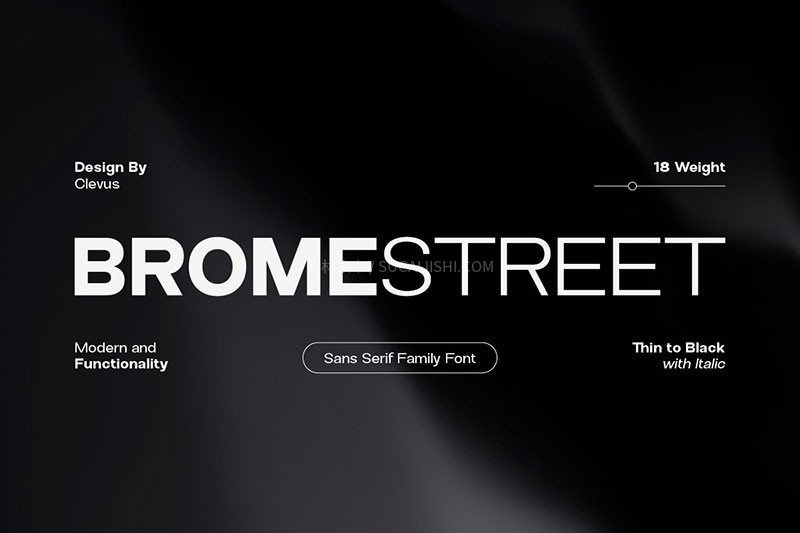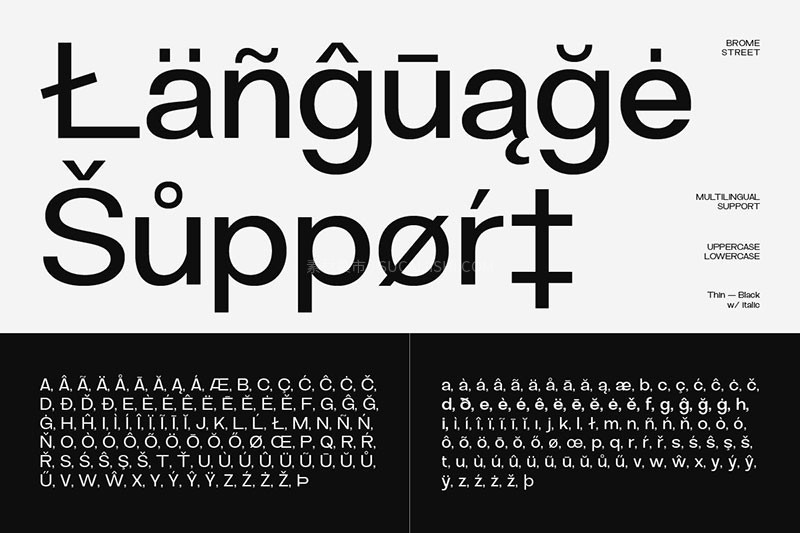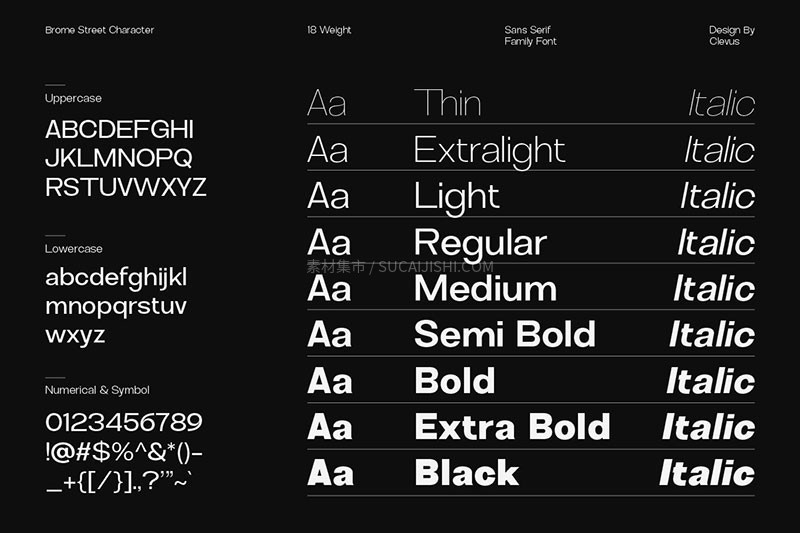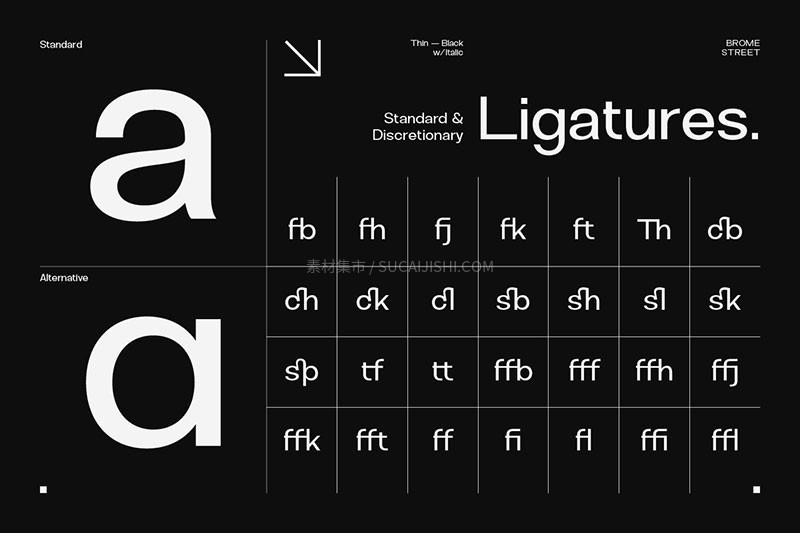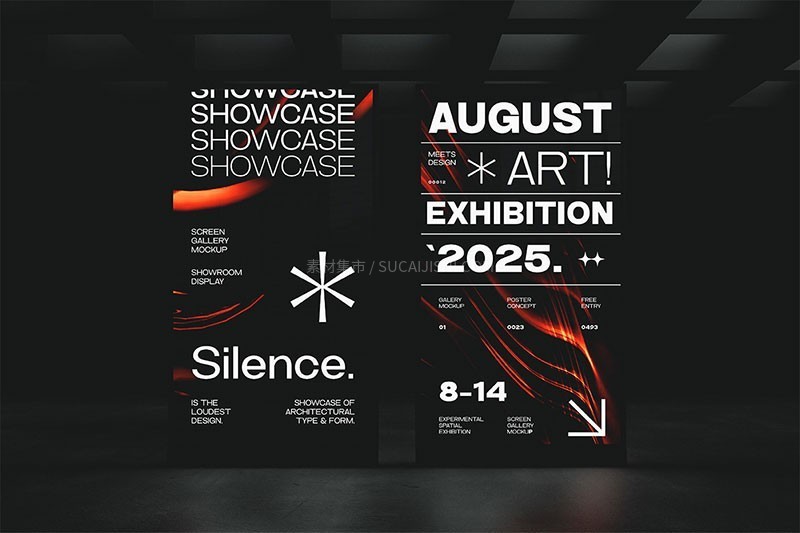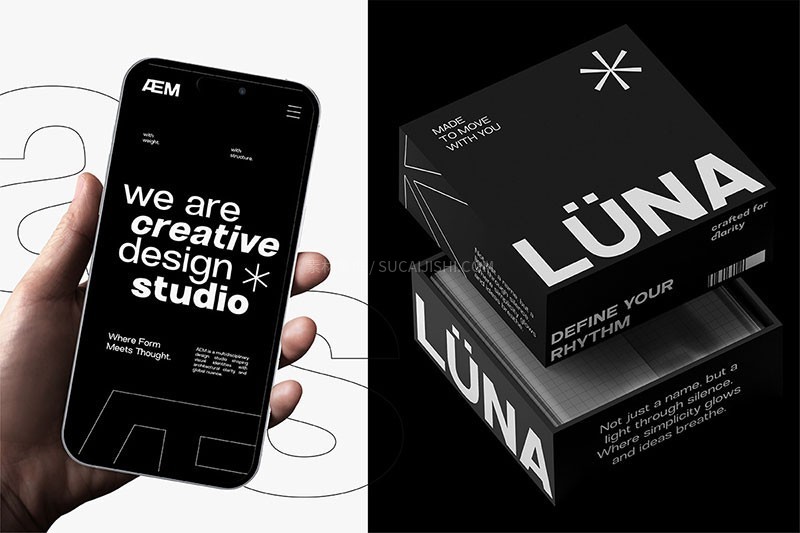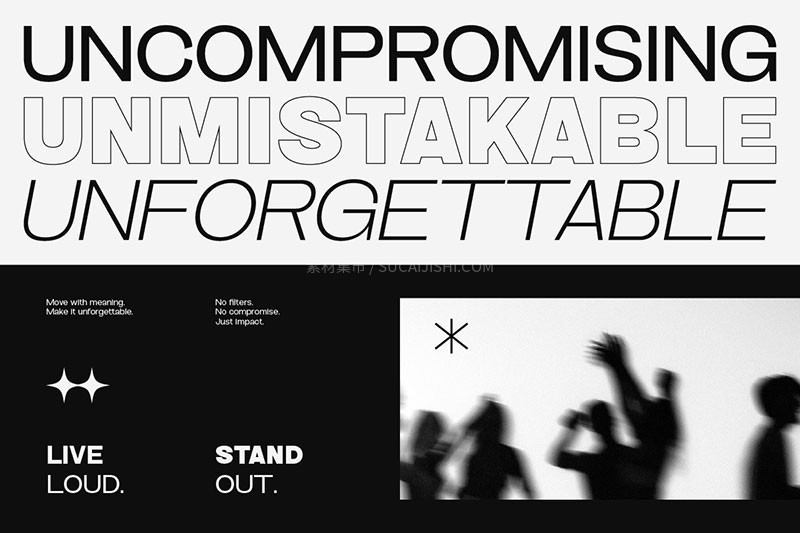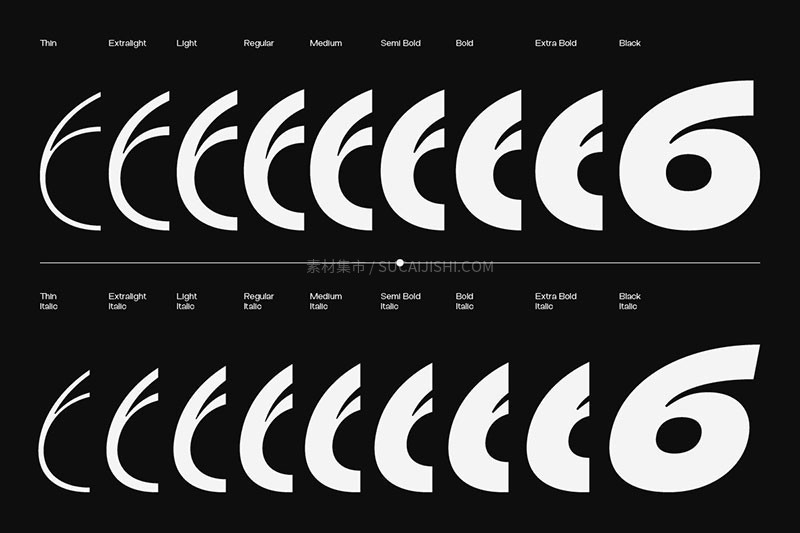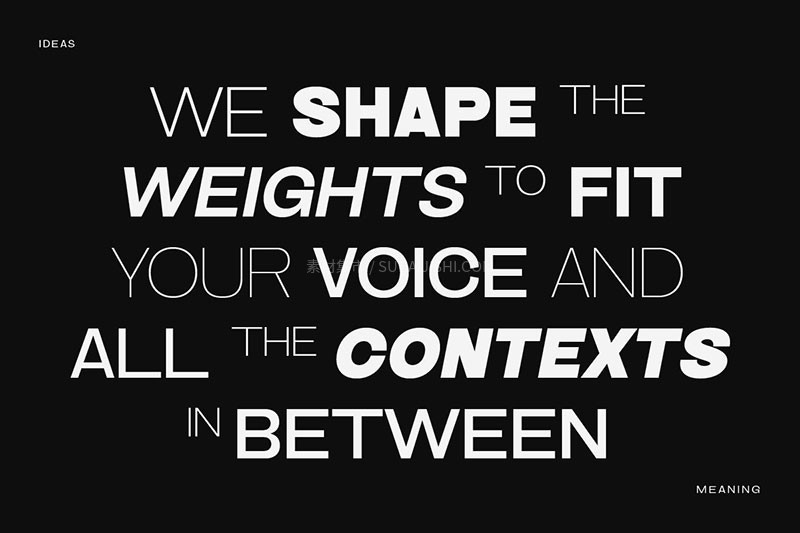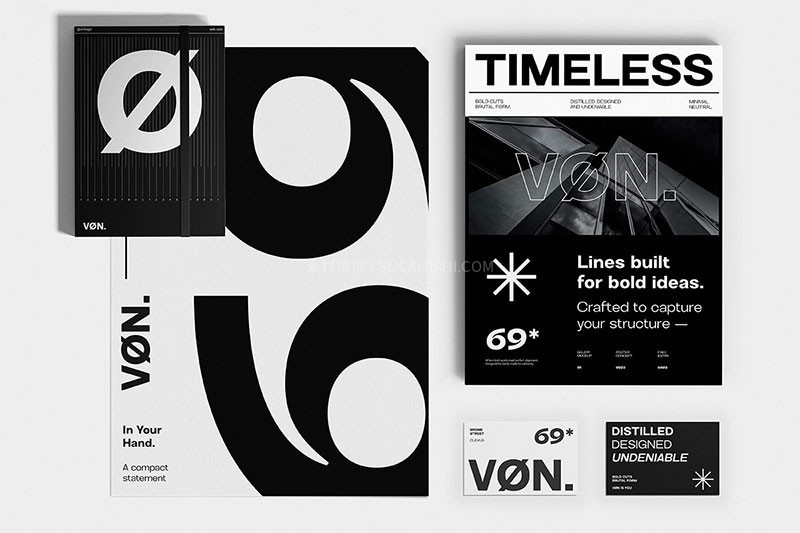
Brome Street Family 经典无衬线字体
一款现代、大胆且极具表现力的窄体字体家族。它以经典字体为灵感,提供了多达18种不同粗细的字重,从纤细到粗壮,让你的设计在任何尺寸下都充满力量感和视觉冲击力。无论是用于醒目的标题、海报、品牌标识,还是需要强调个性的创意项目,Brome Street Family都能轻松驾驭,赋予作品独特的现代美感。
用这个动感倾斜的字体做运动健身的海报超带感,感觉随时都要跑出画面一样。